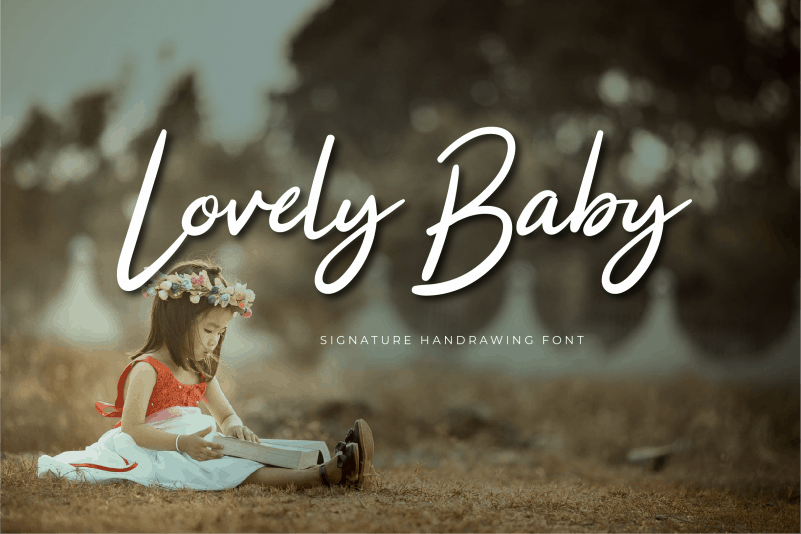
Lovely Baby Calligraphy Font – Fonte Grátis
Lovely Baby Calligraphy Font
A fonte ‘Lovely Baby Calligraphy Font’ é uma beleza que resulta do acasalamento de encanto entre um canuto e uma caneta fina. Esta fonte adocicada e única, criada à mão, tem uma aparência tão encantadora e autêntica que ela faz qualquer projeto DIY ganhar vida e expressar sua personalidade de maneira inigualável. Este é mais do que apenas uma fonte; ele é um complemento perfeito para aqueles que buscam manter seu trabalho autêntico, tanto quanto elegante. Perfecta para criar frases lindas em blocos de confecção e decorações personalizadas, ou qualquer outro projeto em que deseje exibir sua delicadeza única e encantadora.